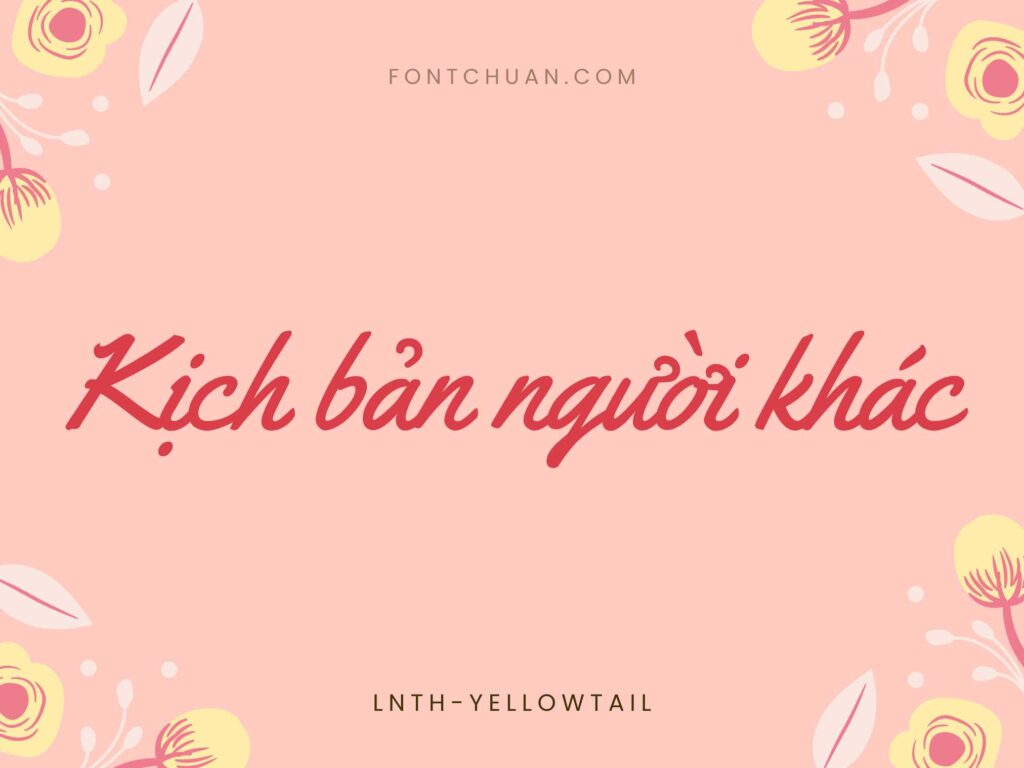
Font LNTH Yellowtail Việt Hóa
Font Yellowtail là một font chữ mang phong cách viết tay cổ điển, lấy cảm hứng từ kiểu chữ script Mỹ những năm 1930. Với những đường nét uyển chuyển, mềm mại, Yellowtail mang đến cảm giác hoài cổ nhưng vẫn giữ được sự hiện đại, phù hợp để sử dụng trong các thiết kế mang hơi hướng vintage, retro hoặc branding chuyên nghiệp.
Phiên bản này đã được Việt hóa bởi LNTH, hỗ trợ đầy đủ tiếng Việt cùng hơn 50 ngôn ngữ khác, giúp người dùng dễ dàng ứng dụng trong thiết kế quốc tế. Font Yellowtail được các thành viên Font Chuẩn sưu tầm và đăng tải nhằm cung cấp một lựa chọn tuyệt vời cho các nhà thiết kế đang tìm kiếm một font script có nét thanh lịch và mềm mại.
Về đặc điểm thiết kế, Yellowtail có độ dày vừa phải, các nét cong mượt mà, tạo cảm giác tự nhiên như chữ viết tay thực tế. Nhờ sự thanh thoát và bay bổng của mình, font này rất thích hợp để dùng trong các thiết kế liên quan đến thương hiệu, quảng cáo, bao bì sản phẩm, thiệp cưới, và các nội dung sáng tạo khác.
Font Yellowtail được ứng dụng rộng rãi trong các sự kiện như Valentine, Thiệp cưới, hoặc các thiết kế mang phong cách cổ điển. Nó phù hợp với nhiều ngành nghề như quảng cáo, thiết kế thương hiệu, spa, ẩm thực, và in ấn sáng tạo.